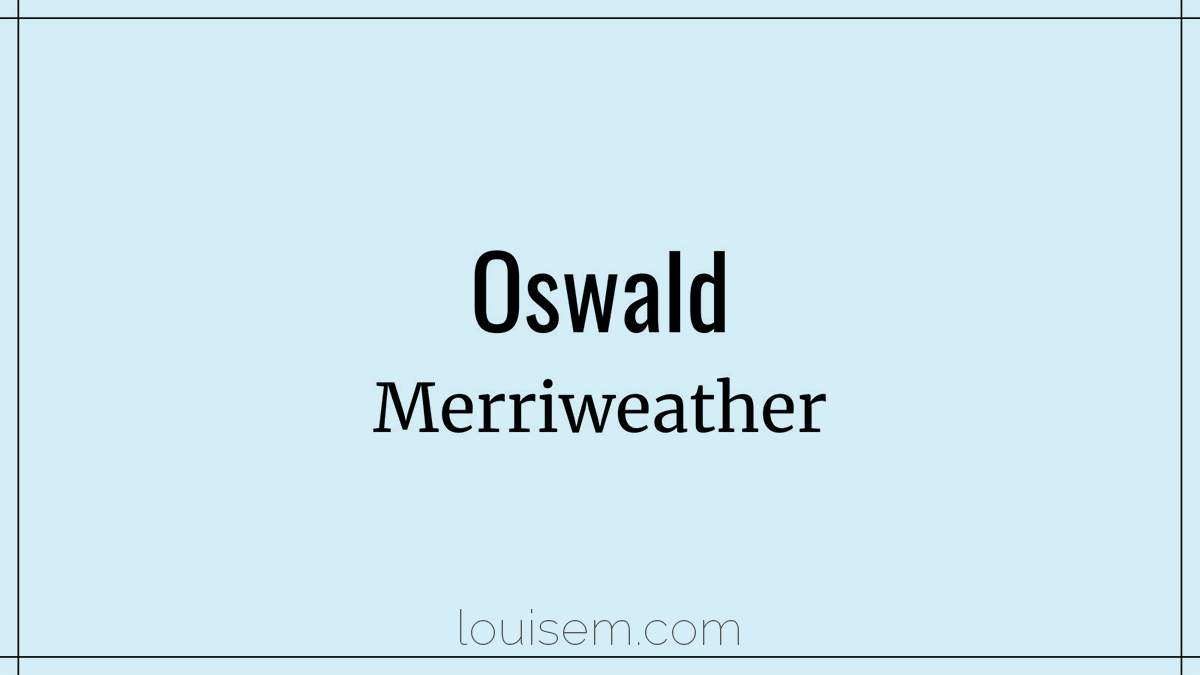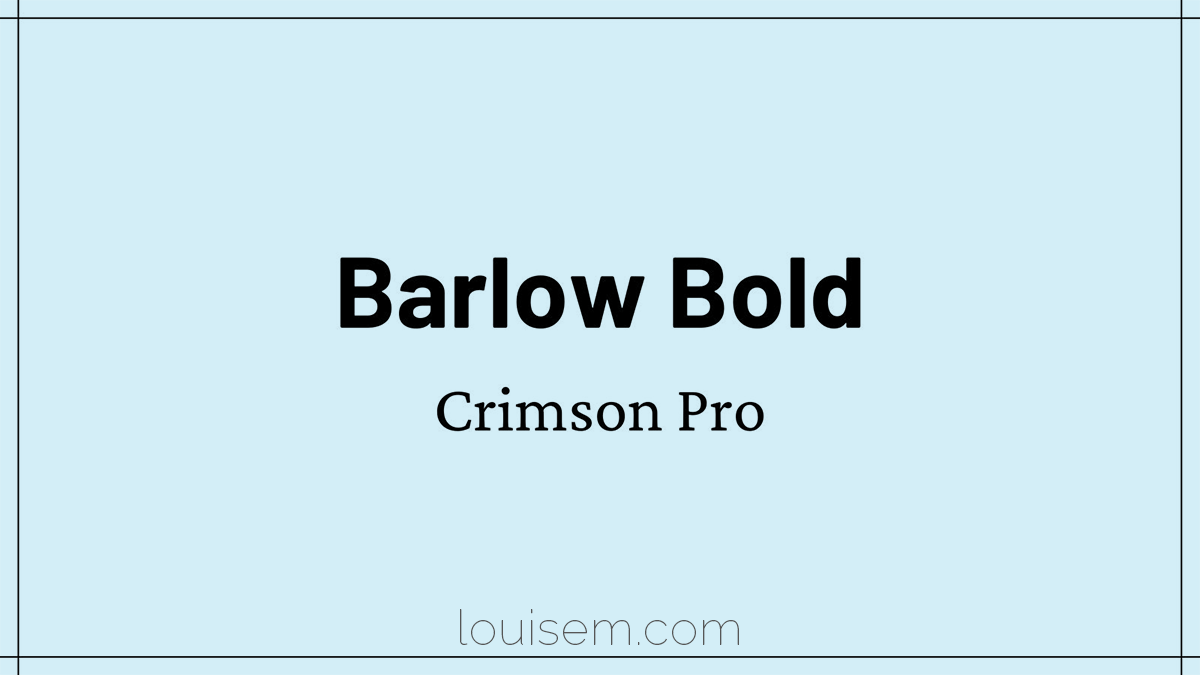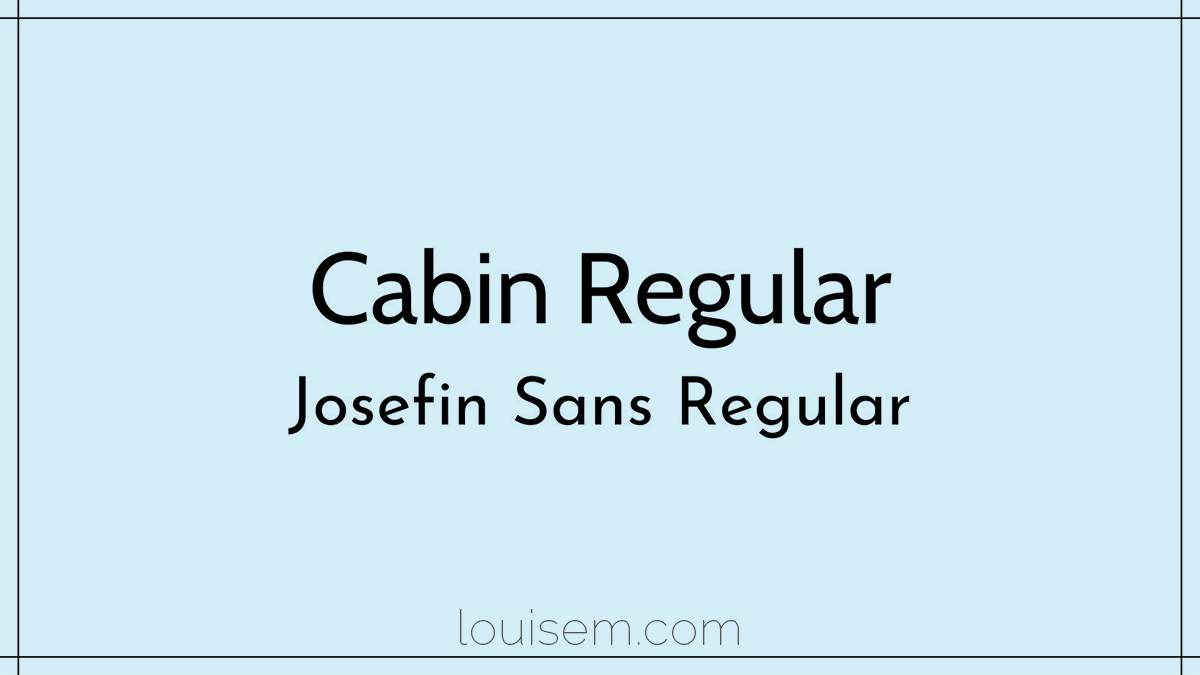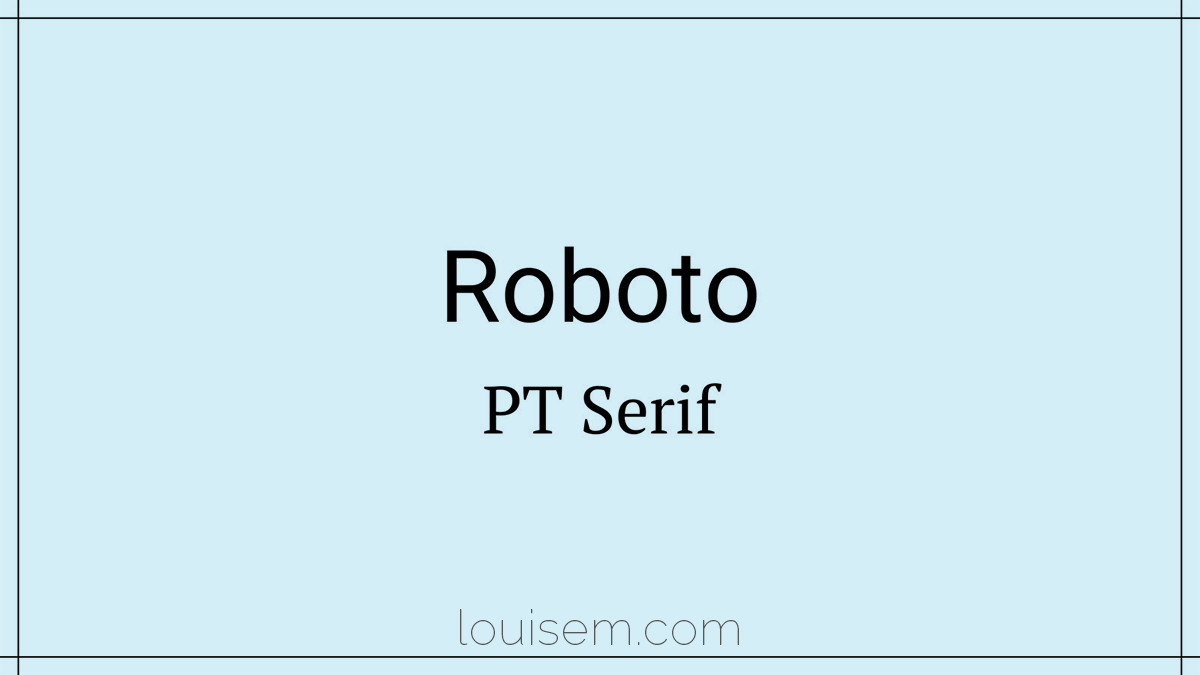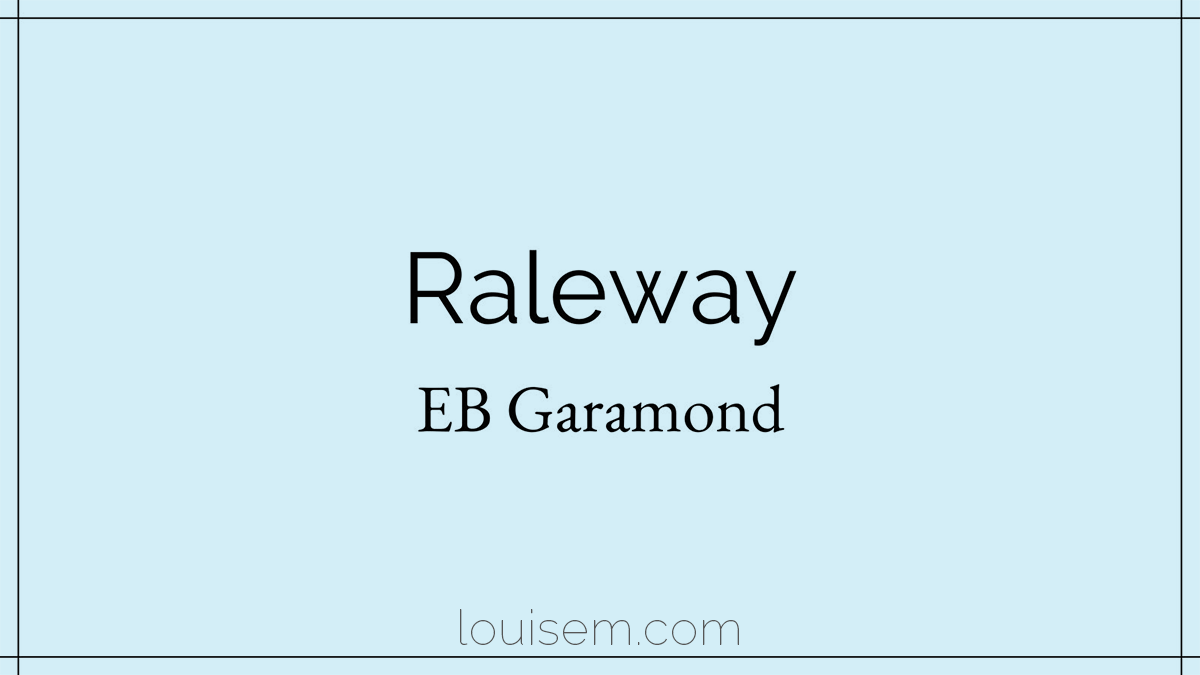
10 лучших сочетаний шрифтов Canva для выдающихся дизайнов в 2023 году
Опубликовано: 2022-11-19Любите использовать Canva, но застряли, когда дело доходит до комбинаций шрифтов?
Хорошо продуманный текст — ничто без отличных шрифтов.
Выбранные вами шрифты могут создать или разрушить ваш дизайн, поэтому важно знать, какие из них хорошо сочетаются друг с другом.
В Canva есть множество замечательных шрифтов, как для бесплатных, так и для профессиональных пользователей.
Давайте посмотрим на некоторые из лучших сочетаний шрифтов Canva и на то, что делает их такими популярными.
Плюс как и когда их использовать!
Анатомия шрифтов
Прежде чем вы сможете комбинировать шрифты, вам нужно немного узнать о дизайне шрифтов!
Шрифты обычно сгруппированы в три основных типа:
Шрифты с засечками имеют небольшие выступы на концах букв. Эти маленькие «ножки» делают слова легко читаемыми для основного текста. Полезно знать, если вы создаете электронную книгу в Canva!
Шрифты без засечек не имеют штрихов в конце букв или других украшений. Обычно это современные шрифты.
В рукописных шрифтах буквы связаны вместе, чтобы они выглядели более рукописными. Рукописные и курсивные шрифты лучше всего использовать для заголовков и шрифтов.
Шрифт также состоит из множества различных частей, каждая из которых влияет на его общий вид:
- Высота прописных букв равна высоте заглавных букв.
- x-height — это высота строчных букв.
- Базовая линия — это воображаемая линия, на которой лежат все буквы.
- Нисходящий элемент — это часть буквы, которая выступает ниже базовой линии.
- Основа — основной вертикальный штрих в письме.
Как разные шрифты говорят с вами
В любой форме маркетинга выбранный вами шрифт многое говорит о вашем бренде.
Шрифты могут быть игривыми или серьезными, современными или традиционными, громкими или сдержанными. Правильный шрифт может помочь вам привлечь внимание вашей целевой аудитории и передать правильное сообщение о вашем бренде.
При выборе шрифта для ваших маркетинговых материалов важно учитывать, как различные варианты будут говорить с вашей целевой аудиторией.
Например, игривый шрифт может хорошо подходить для бренда детских игрушек, а более серьезный шрифт больше подходит для фирмы, предоставляющей финансовые услуги.
В конечном счете, цель состоит в том, чтобы выбрать шрифт, который поможет вам связаться с вашей целевой аудиторией и передать правильное сообщение о вашем бренде.
Как эффективно использовать шрифты
Правильный шрифт может помочь передать желаемый тон и сообщение вашего бренда, в то время как неправильный шрифт может оттолкнуть потенциальных клиентов.
Вот несколько советов по эффективному использованию шрифтов в маркетинговых материалах:
Будь проще
Выбирая шрифт, выбирайте что-то легко читаемое.
Вы хотите, чтобы потенциальные клиенты могли быстро просмотреть ваши материалы и понять ваше сообщение.
Избегайте использования нескольких шрифтов
Использование слишком большого количества разных шрифтов может сбить вас с толку и сделать ваши материалы загроможденными.
Придерживайтесь одного или двух шрифтов для максимального эффекта.
Учитывайте свою аудиторию
При выборе шрифта подумайте о том, кого вы пытаетесь охватить своими маркетинговыми материалами.
Например, если вы продаете детям, вы можете использовать игривый шрифт. Более серьезный шрифт был бы более привлекательным для взрослых.
Тестируйте разные шрифты
Не бойтесь экспериментировать с разными шрифтами, пока не найдете тот, который передает правильный тон вашему бренду. Иногда требуется немного проб и ошибок, чтобы найти идеальное сочетание.
Лучшие сочетания шрифтов Canva
Спартанская лига и Либре Баскервиль
League Spartan — это современный шрифт без засечек, который привлекает внимание для заголовков.
В сочетании со шрифтом с засечками Libre Baskerville он создает отличный контраст.
Используйте шрифт с засечками для основного текста с этим сочетанием для достижения наилучших результатов.
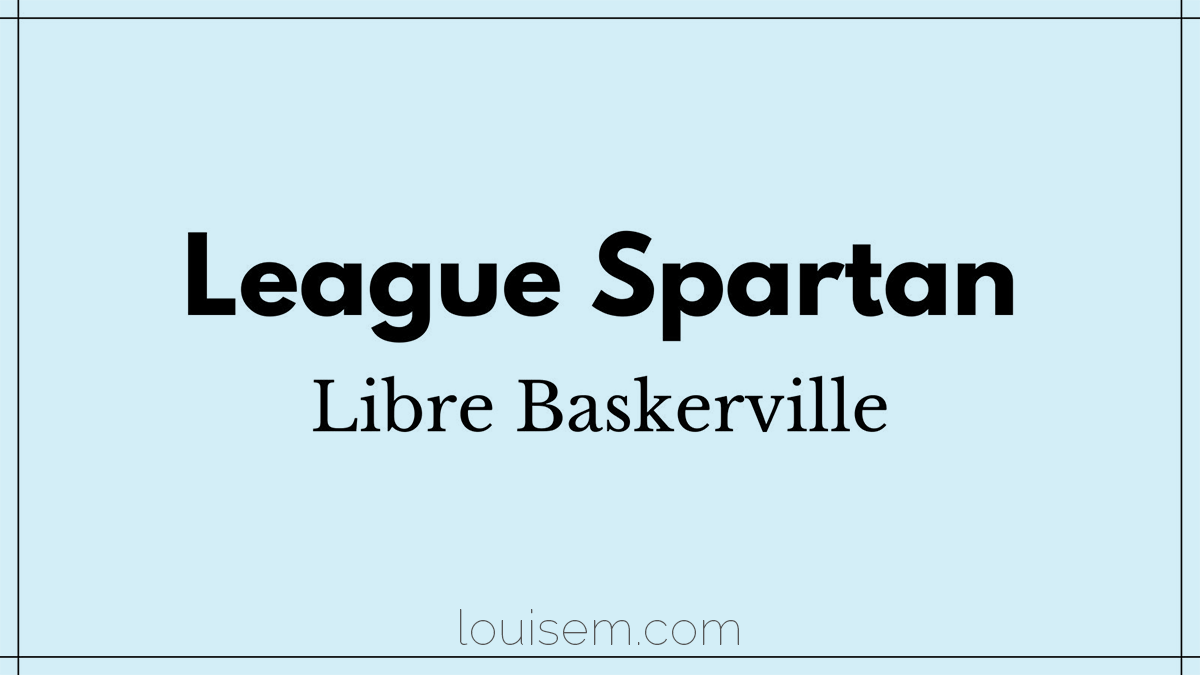
Bodoni FLF и подпись
Bodoni — шрифт с сильными засечками для заголовков, который очень привлекает внимание.
Он хорошо работает с Signature, который является скриптовым шрифтом.
Но используйте его с осторожностью, так как его будет нелегко читать на маленьких экранах.
Соедините их с простым шрифтом без засечек.
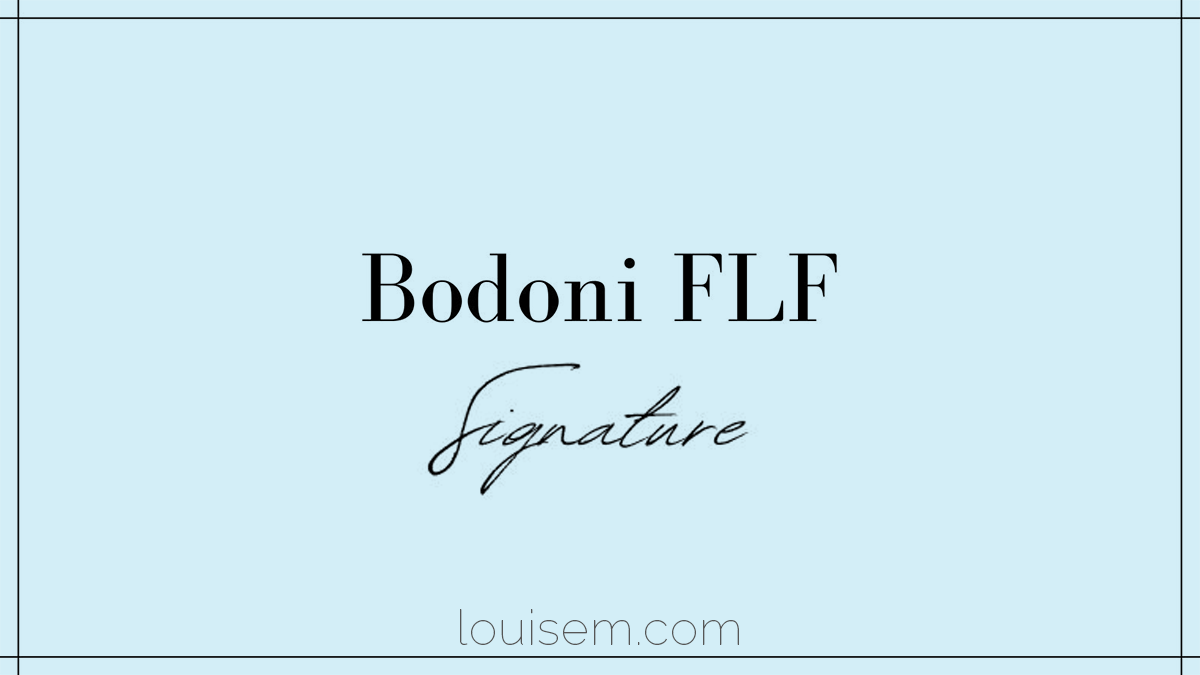
Archivo Black и Archivo Narrow
Это отличный пример двух шрифтов, которые имеют одинаковую гарнитуру, но выглядят по-разному.
Жирную черную версию трудно не заметить, в то время как узкая версия лучше подходит для большего количества текста.
Эта комбинация особенно хороша для проектов, ориентированных на активность, таких как спорт.
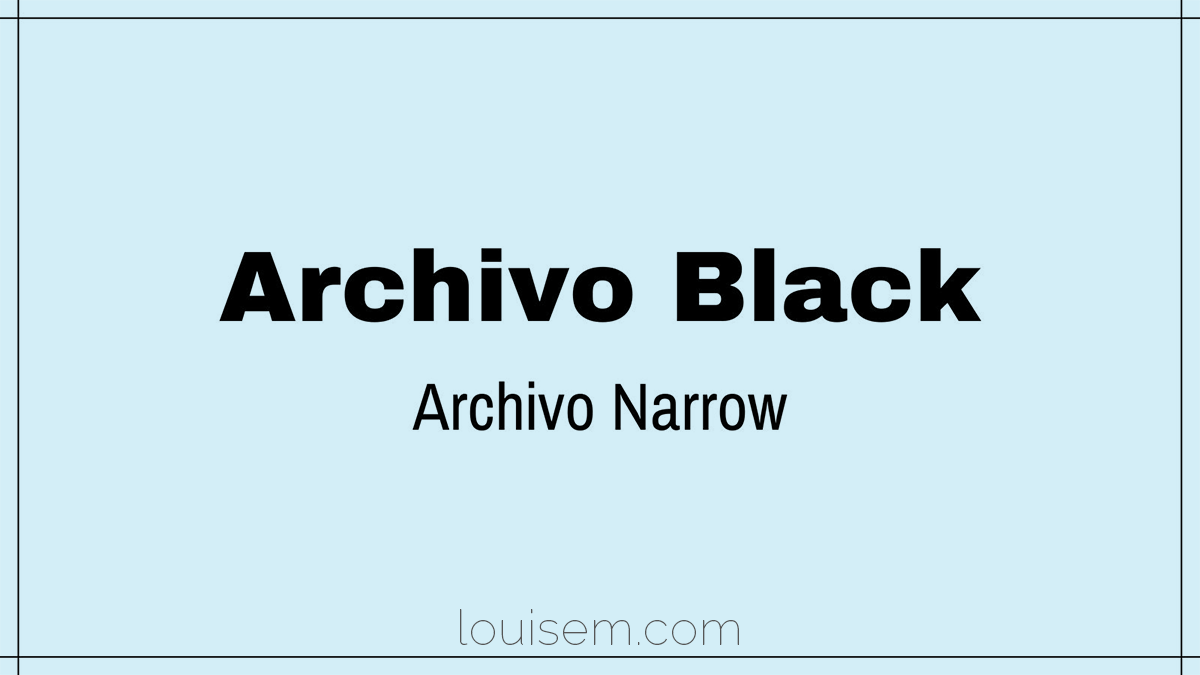
Комбинации шрифтов Canva — отличный способ добавить индивидуальности вашему дизайну.
Экспериментируя с разными шрифтами, вы сможете найти идеальную комбинацию, которая точно представляет ваш бренд.
Пробовать комбинации шрифтов внутри Canva — это простой способ определить, какие шрифты Canva подходят друг другу. Просто не забывайте использовать максимум два или три шрифта.